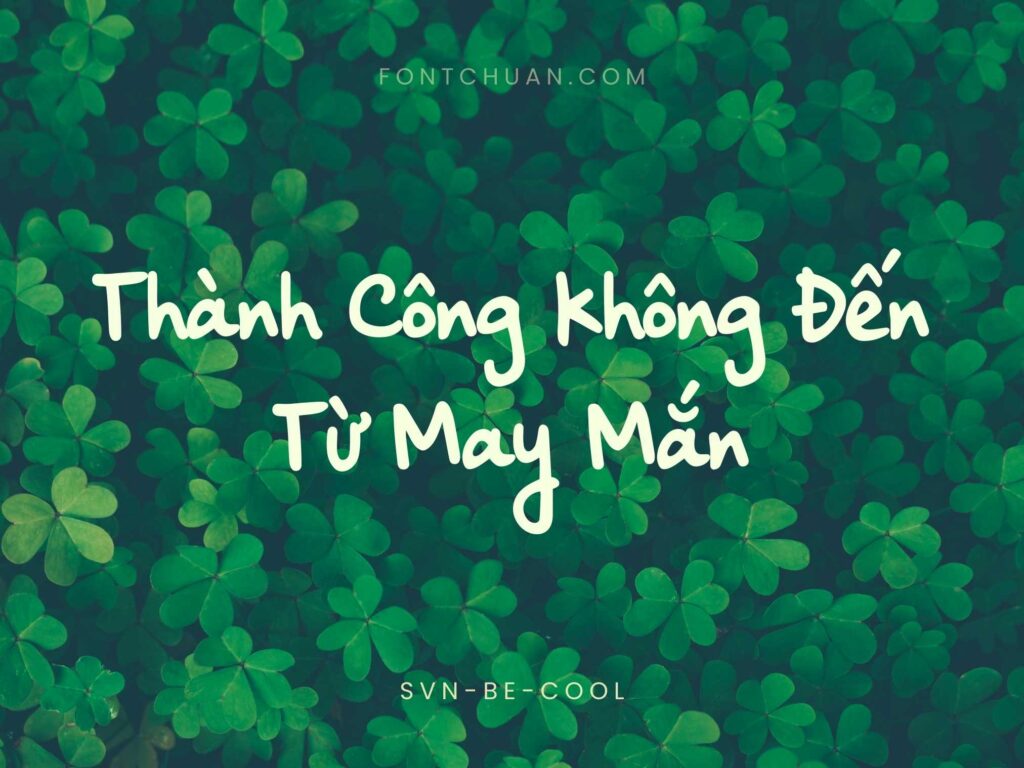
Font SVN Be Cool +Swashes Việt Hóa
Be Cool là một font chữ viết tay được thiết kế bởi Ana Parracho và phát hành bởi Ana’s Fonts vào năm 2018. Font này mang phong cách thân thiện và vui tươi, với các đường nét mềm mại và tự nhiên, tạo cảm giác gần gũi và ấm áp cho người xem. Be Cool bao gồm ba phong cách: Regular, Alternate và Swashes, cung cấp sự linh hoạt cho các nhà thiết kế trong việc tạo ra những tác phẩm độc đáo. Font đã được Việt hóa để hỗ trợ tiếng Việt bởi Styleno.1 Fonts, đồng thời hỗ trợ nhiều ngôn ngữ khác, giúp mở rộng phạm vi sử dụng trên toàn cầu. Font này được thành viên của Font Chuẩn sưu tầm và chia sẻ, đáp ứng nhu cầu của bạn đọc và ứng dụng thực tế vào các dự án thiết kế.
Đặc điểm thiết kế của Be Cool bao gồm các đường nét viết tay tự nhiên, với các ký tự hơi nghiêng và không đồng đều, tạo nên sự chân thực và sống động. Font này phù hợp cho các ứng dụng như thiết kế thiệp mời, logo, tiêu đề, bao bì sản phẩm và các dự án sáng tạo khác. Các ngành nghề phù hợp bao gồm quảng cáo, nghệ thuật, giáo dục và thời trang.